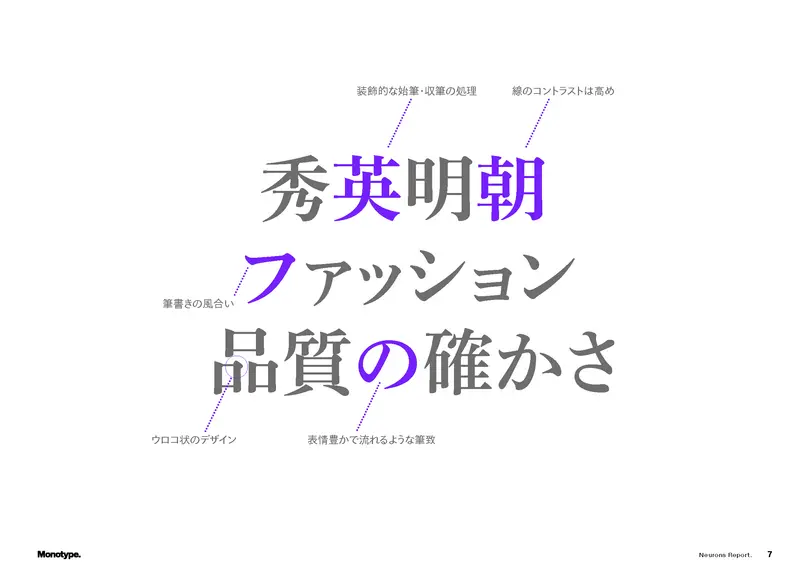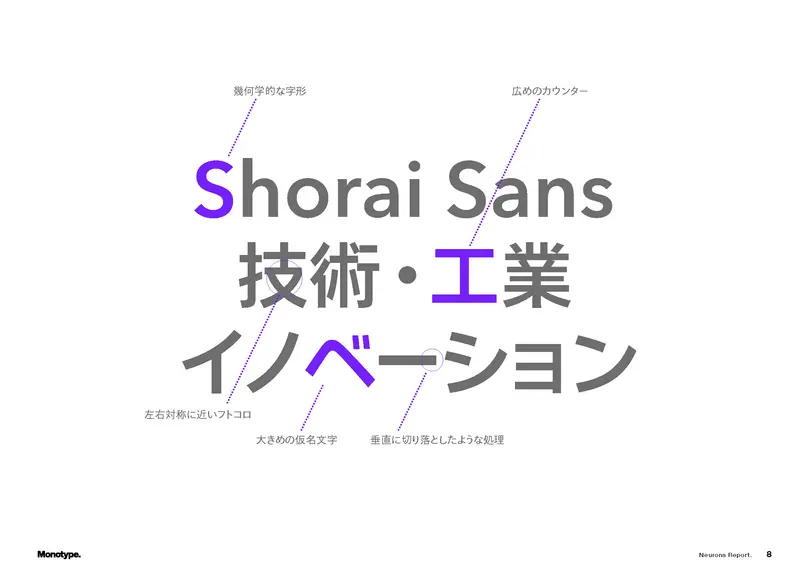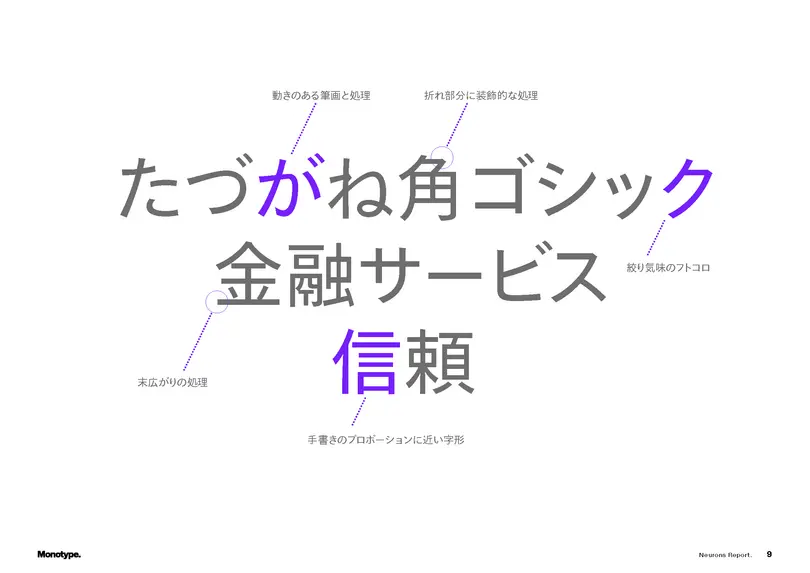
書体はなぜ人の心を動かすのか
デザイナーもブランドの専門家も、その理由は正確に説明で きなくても、書体が人の感情に影響を与えることは以前から 知っていました。書体の使い方が適切でないと、消費者はそ れを本能的に感じ取ります。書体は無意識のうちに感情に影 響を与えます。ただ、それを数値化するのは難しいことです。 高速道路の標識の書体が Comic Sans だったら指示に従いますか? Papyrus を使っている保険会社の住宅保険に入りますか? もししないとしたら、それはなぜなのでしょうか。
こんな経験はありませんか―住宅ローンの借り換えや他の 保険会社への乗り換えを勧める手紙、メールが来た。一見特 に問題はなさそうだけれど、何か違和感が。よく見ると品質の悪いフォントが使われている。そして思わずこんなことが 頭をよぎります―「もしかして、詐欺?」
ブランドは書体を通して信頼、誠実さ、確実性を伝えます。たとえロゴや写真、グラフィックデザイン、UIデザインに非の打ち所がなくても、見た人が書体が合っていないと感じた瞬間、不信感や不安感が生まれます。
デザイナーもブランドの専門家も、その理由は正確に説明できなくても、書体が人の感情に影響を与えることは以前から知っていました。書体の使い方が適切でないと、消費者はそれを本能的に感じ取ります。書体は無意識のうちに感情に影 響を与えます。ただ、それを数値化するのは難しいことです。 高速道路の標識の書体が Comic Sans だったら指示に従いま すか? Papyrus を使っている保険会社の住宅保険に入りますか? もししないとしたら、それはなぜなのでしょうか。
Monotype は、神経科学の観点から消費者行動を調査する Neurons 社と共同で、書体が感情を左右するという私たちが長年信じてきた考えが正しいのかどうか、実際に人間の感情に影響を与えるのかどうか、実験・検証を行いました。私たちはこのプロジェクトを通じて、書体がどのように経験、連想、感情を引き起こすのかを理解し、使用場面に応じた書体の有効性について評価したいと考えました。 書体はタグラインやスローガンへの私たちの反応に影響を与えることができるのでしょうか。企業ロゴのより肯定的な見方を促すことができるのでしょうか。そして、ブランドと消費者との間に実際に信頼関係を築くことができるのでしょうか。
タイポグラフィでよく直面する問題は、なぜそんなに重要なのかということです。一般の人たちにとって、業界以外の友人や家族にとって、そして、あなたが舵取りや影響力の発揮で力を貸そうとしている企業の幹部にと ってタイポグラフィがなぜそんなに重要なのか。これに尽きます
調査の方法
Monotype と Neurons は150人を対象に 3 種類の刺激要因(ひとつの言葉、その言葉の入った文章、その言葉とブランド名の入った文章)を使って調査を行いました。それぞれを 3 種類の書体(6 ページ参照)で組み、回答者は各組み合わせを「誠実、印象的、信頼 感、確信」といった感情指標で評価しました。 調査結果は、書体が感情にどう働きかけるのかについての私たちの考えを裏付けるものとなりました。書体の選択だけで人の感じ 方に大きな影響を与えることができ、 調査では肯定的な反応が30%を超えたものもありました。普通は0~5%程度 という中で、このように説得力のある数字が出たことは Neurons にとって驚きでした。
普通は0~5%程度を予想しますが、今回はそれをはるかに上回りました。書体には力があり、人の気持ちに実際に影響を与えることが証明されたのです。とても興味深いことです。
次の段階へ
同じ調査を他の国や言語で実施したらどうなるのか。英語で期待通りの結果が得られた私たちは、同じ「quality、trust、innovation」というブランド価値を表現した単語を使って、日本語を母語とする人への調査を依頼することにしました(調査では「品質の確かさ」「信頼」「イノベーション」という日本語表現を使用)。言語、タイポグラフィ、文化は互いに密接に関わり合っています。果たして結果は異なるのか、異なる場合はどの程度なのかを知りたかったのです。方を促すことができるのでしょうか。そして、ブランドと消費者との間に実際に信頼関係を築くことができるのでしょうか。
神経科学の応用
こうした問いの答えを探るため、Neurons は数十年にわたるデータ収集と消費者神経科学の経験を駆使して、書体に対する人々の意識的・無意識的な反応を測定しました。検証に使用したのは、ヒューマニスト・サンセリフ体の「たづがね角ゴシック」、ジオメトリック・サンセリフ体の「Shorai Sans」、明朝体の「秀英明朝」の 3 書体です。
それぞれがタイポグラフィとデザインの歴史に根ざした特徴ある書体のため、文字の形やその効果といった細かな部分まで比較することができます。書体の選択はブランドのカスタム書体制作の豊富な経験をもとに行われましたが、その目的は自分たちの思い込みをすべて疑ってみることにありました。いずれの書体も見覚えのあるブランドの文字に似ているものの、有名企業を思い起こさせるものではなく、認知度としてはちょうど良いものです。既存のブランドデザインを無意識に連想させることを避けることができます。